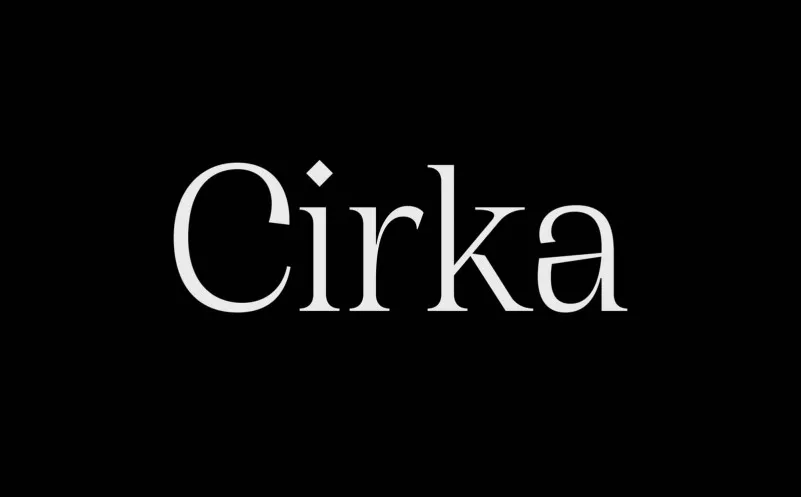
A Cirka Typeface é uma elegante tipografia serifada criada por Nick Losacco que combina linhas suaves com serifs aguçados. Esta fonte tem uma estrutura reduzida e personalidade peculiar, fazendo-a ideal para ambientes de destaque e exibição. Suas formas amplos permitem criar expressões vivas em múltiplas opções de estilo, tornando-se um recurso valioso tanto para o texto principal quanto para grandes títulos ou posters. Sua versão leve até a grossa permite utilização em diferentes contextos de leitura e exibição, seja grande na parede ou pequena no texto do corpo. Este é uma fonte muito versátil que certamente enriquecerá o design gráfico.